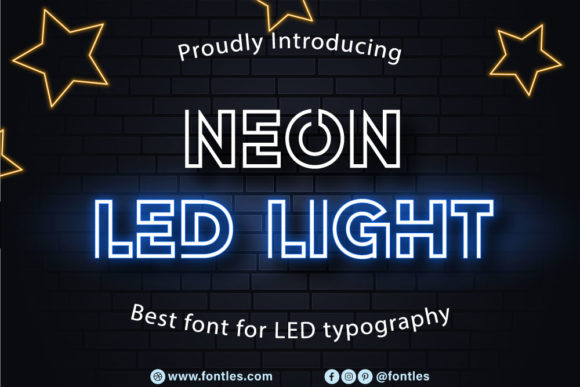
Creativefabrica Neon Led Light Font
[Creativefabrica] Neon Led Light Font
Neon Led Light - невероятно уникальный и футуристичный шрифт.
Мастерски разработанный, чтобы стать настоящим фаворитом, этот шрифт способен поднять каждую вашу творческую идею на самый высокий уровень!